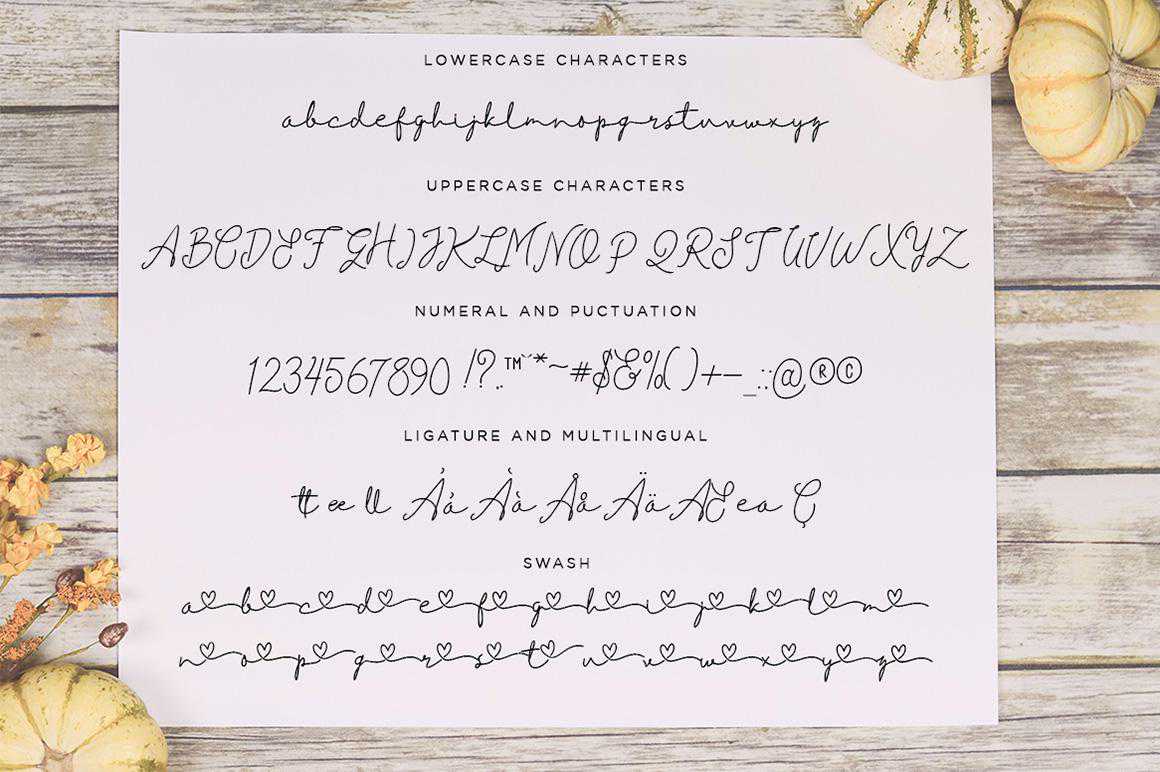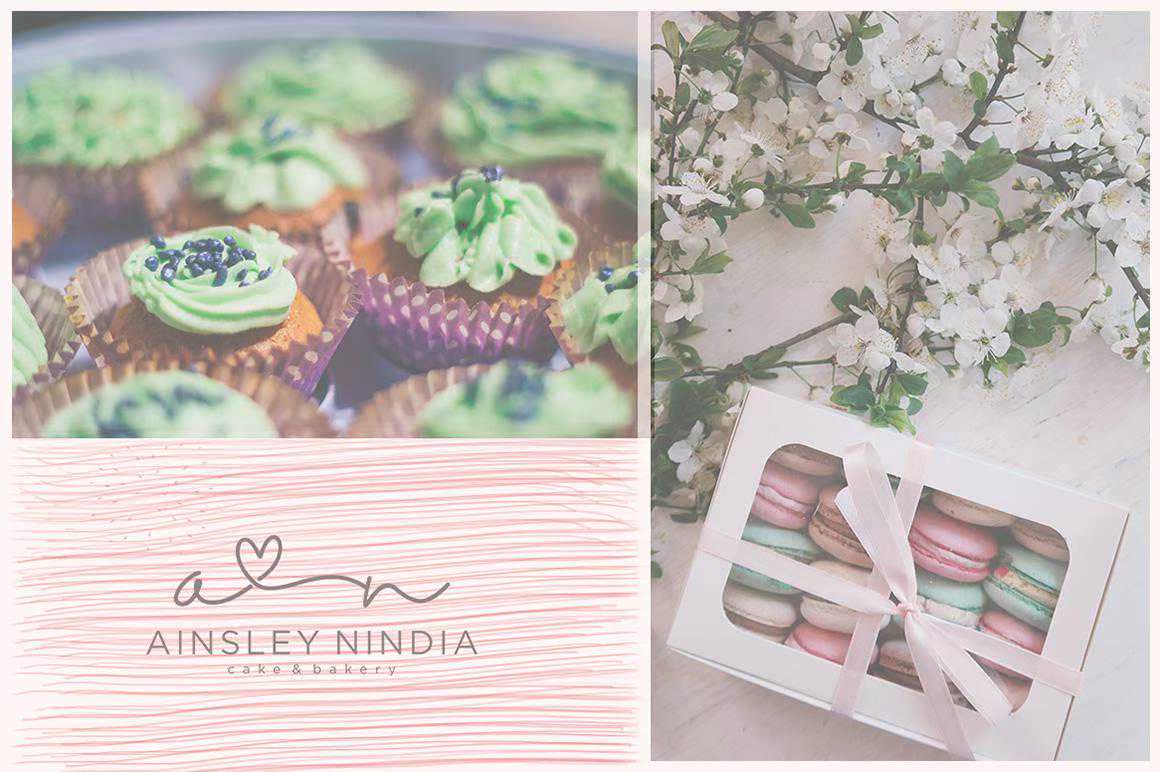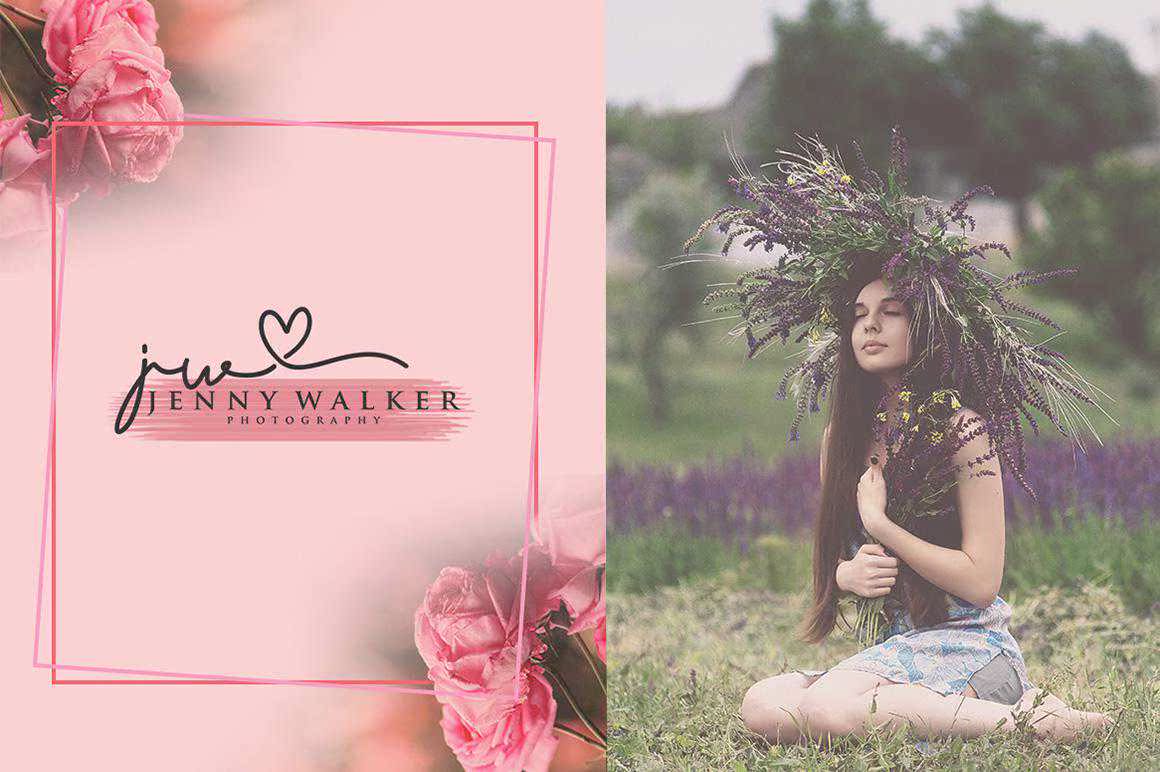
Diahlova Demoversion FontIsa手写签名描述了自然和样式流。Diahlova FontOf脚本是个人品牌的完美选择。Diahlova是品牌项目、徽标、婚礼设计、社交媒体、广告、产品包装、产品设计、标签、照片、水印、邀请、,和文具。Diahlova Demoversion Font是手写签名,而非自然和样式流。Diahlova FontOf脚本是个人品牌的完美选择。Diahlova是品牌项目、徽标、婚礼设计、社交媒体、广告、产品包装、产品设计、标签、照片、水印、邀请和文具的完美选择。